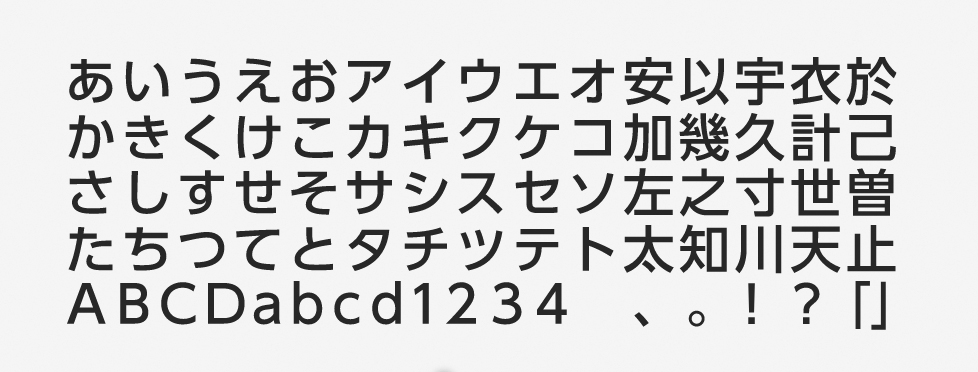
「UD新ゴ」について
モリサワUD(ユニバーサルデザイン)フォントの1つで、現代的なデザインの新ゴをベースとして開発されています。ユニバーサルデザインに配慮されたUDフォントらしく、文字のかたちが分かりやすく、文章を読みやすくて、誤読も起こしにくいフォントです。可視性や可読性が高いので、特に現代のニーズやトレンドに合致したフォントと言えるでしょう。
「UD新ゴ」の特徴
もともと新ゴは見やすさに定評のあるフォントでしたが、UD新ゴではさらに文字それぞれの分かりやすさを重視した字形が追求されました。英数字にはClearTone SGのデザインが採用されており、判別性の高さが特徴です。
新ゴは字面が大きいため、長文を組むとやや窮屈な印象に見えることもありますが、UD新ゴでは漢字とかな文字の字面の大きさに差がつけられています。これにより誰にとっても長文を読みやすく、文章の中でそれぞれの文字もしっかりと見えます。
UD新ゴは特に英数字のデザインが優れていますね。ユニバーサルデザインに対応しつつ、美しい文字です。通常の新ゴと比べて大幅にイメージも変わりました。さまざまな場面で、ぜひ利用をオススメしたいフォントです。